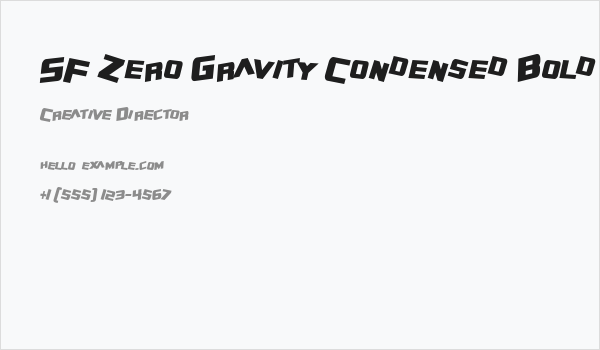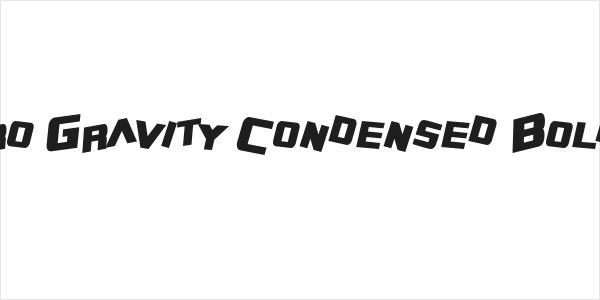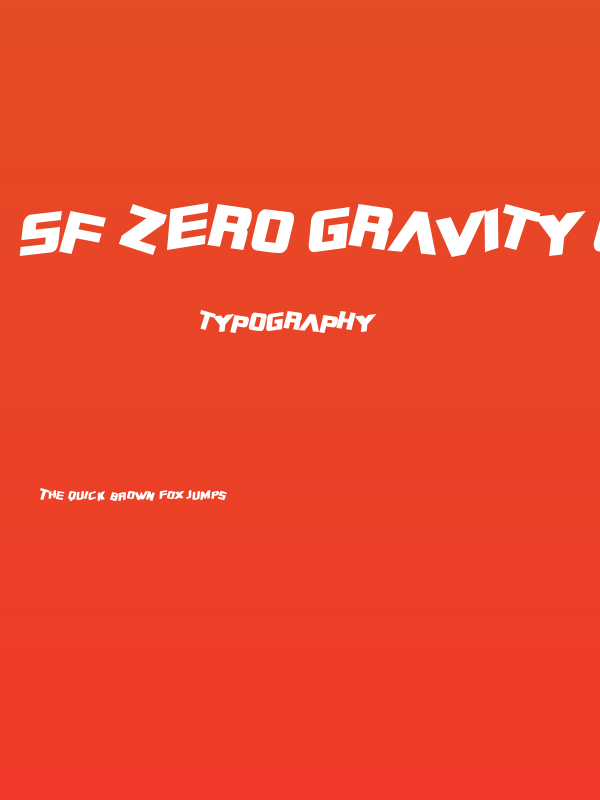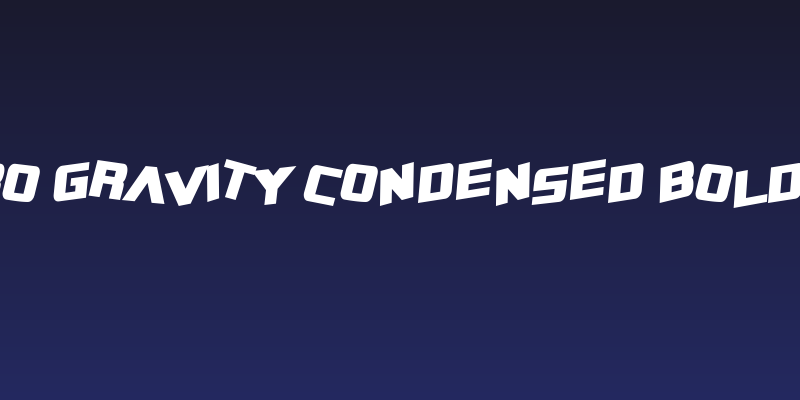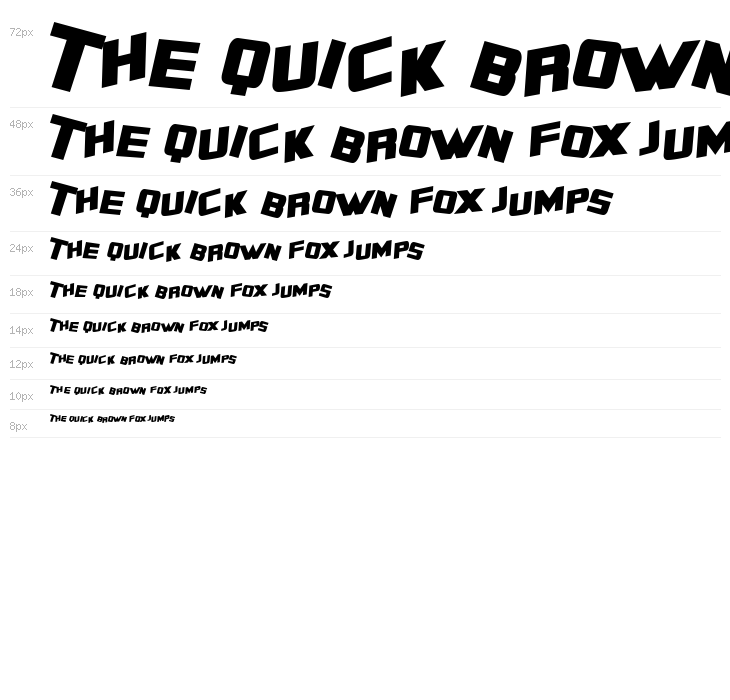
SF Zero Gravity Condensed Bold Italic Font
✎ Wavy
| Progetti proposti | Ideal for sci-fi themed posters, video game titles, tech branding, and dynamic advertising campaigns. |